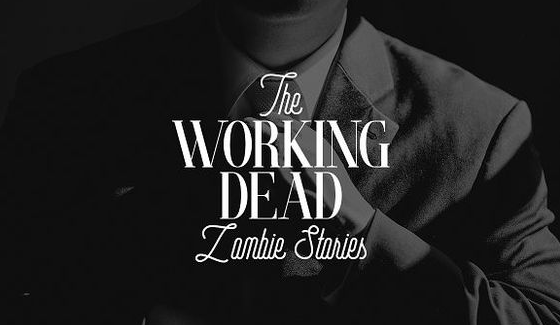
Quixo + Nestle Typeface – Download Grátis
Introduzimos Quixo, uma tipografia serifa ideal para deixar seu texto mais atraente. Esta fonte é perfeita para aplicação em marcas e logotipos, cabeçalhos de textos, anúncios de impressão, roupas, embalagens comerciais, cartões de visitas, entre outros. Seus recursos do OpenType oferecem uma ampla gama de características que permitem escolher a melhor letra para cada projeto. Esses recursos incluem diferentes estilos de negrito e itálico, sobresílabos, ligação de traços e ponteiros de parênteses personalizados. Quixo foi projetada pelo designer 178-MC e está disponível em uma série completa de caracteres aprimorados. Estes incluem códigos alternativos para letras menores (ligar-se), variáveis que permitem ajustes de tamanho, rotas diferentes dos traços, além de um amplo conjunto de opções para sobresílabos. Se você deseja ter acesso à todos os caracteres da fonte Quixo, é necessário usar software que suporta OpenType Features como Adobe Illustrator, InDesign, Photoshop e CorelDraw. A sua escolha certamente impressionará seus clientes ou consumidores finalmente, ao tornar seu texto mais agradável para os olhos.